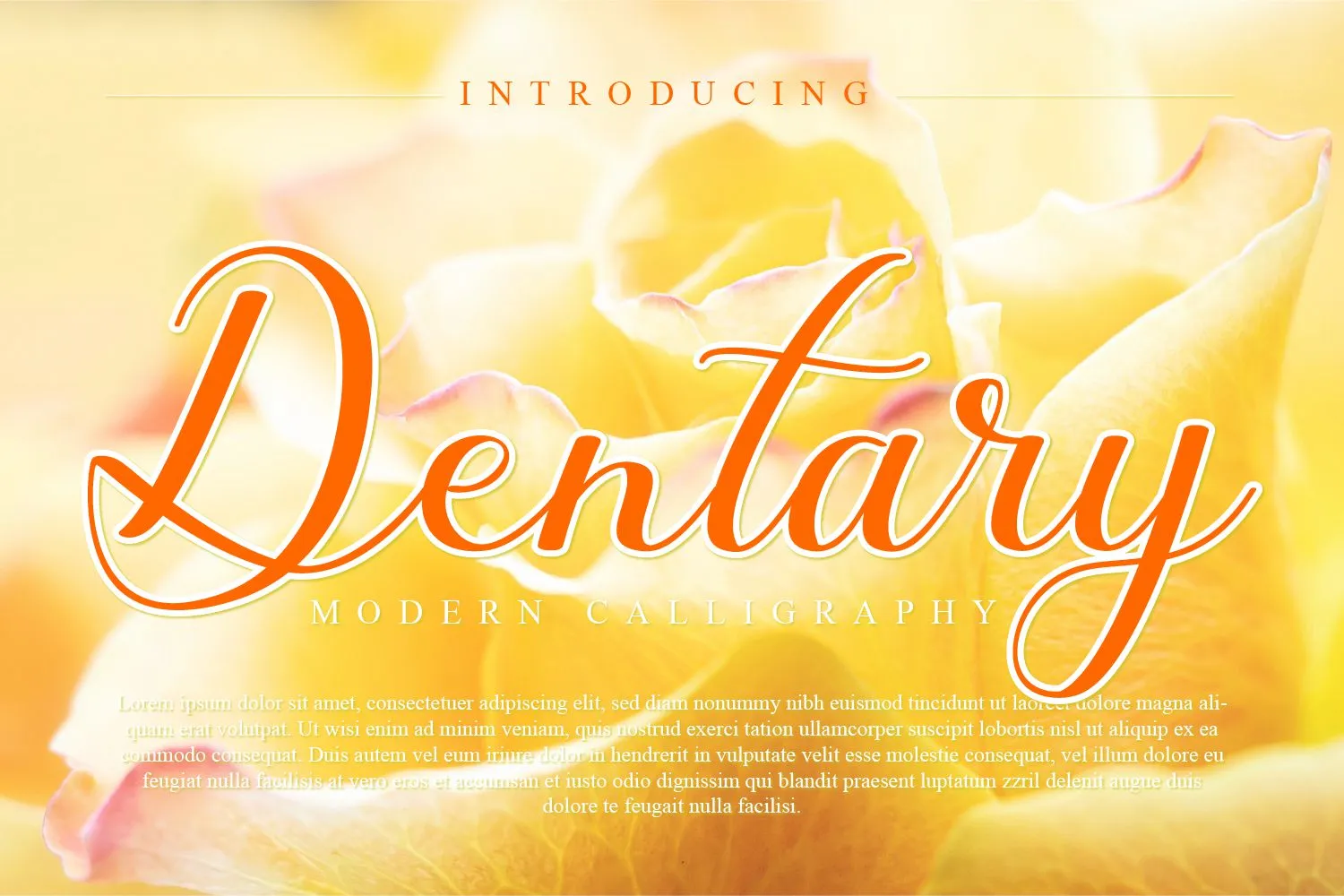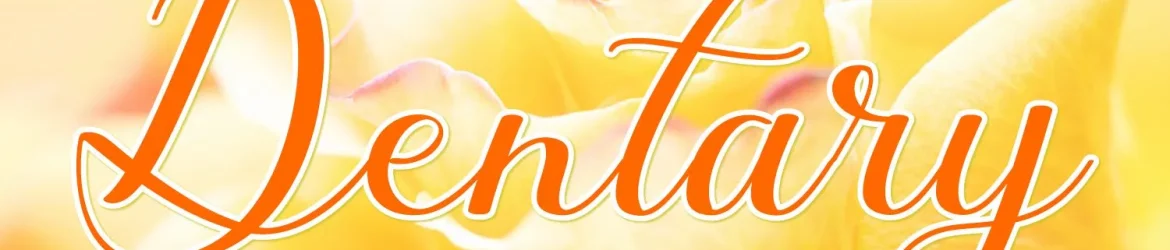
Dentary Font – Download Grátis
A ‘Dentary Font’ é uma delicada tipografia escrita que apresenta personagens encantadores e divertidos que parecem dançar ao longo do paralelepípedo. Seu design leve e alegre se encaixa perfeitamente com trabalhos criativos, tornando-os ainda mais chamativas e distintivos. Esta fonte é como uma paleta de cores vivas para suas ideias inovadoras, potencializando seu trabalho de forma surpreendentemente bonita. Seja para textos ou gráficos, a ‘Dentary Font’ traz vida à sua arte, tornando-a ainda mais especial e única no mundo digital.